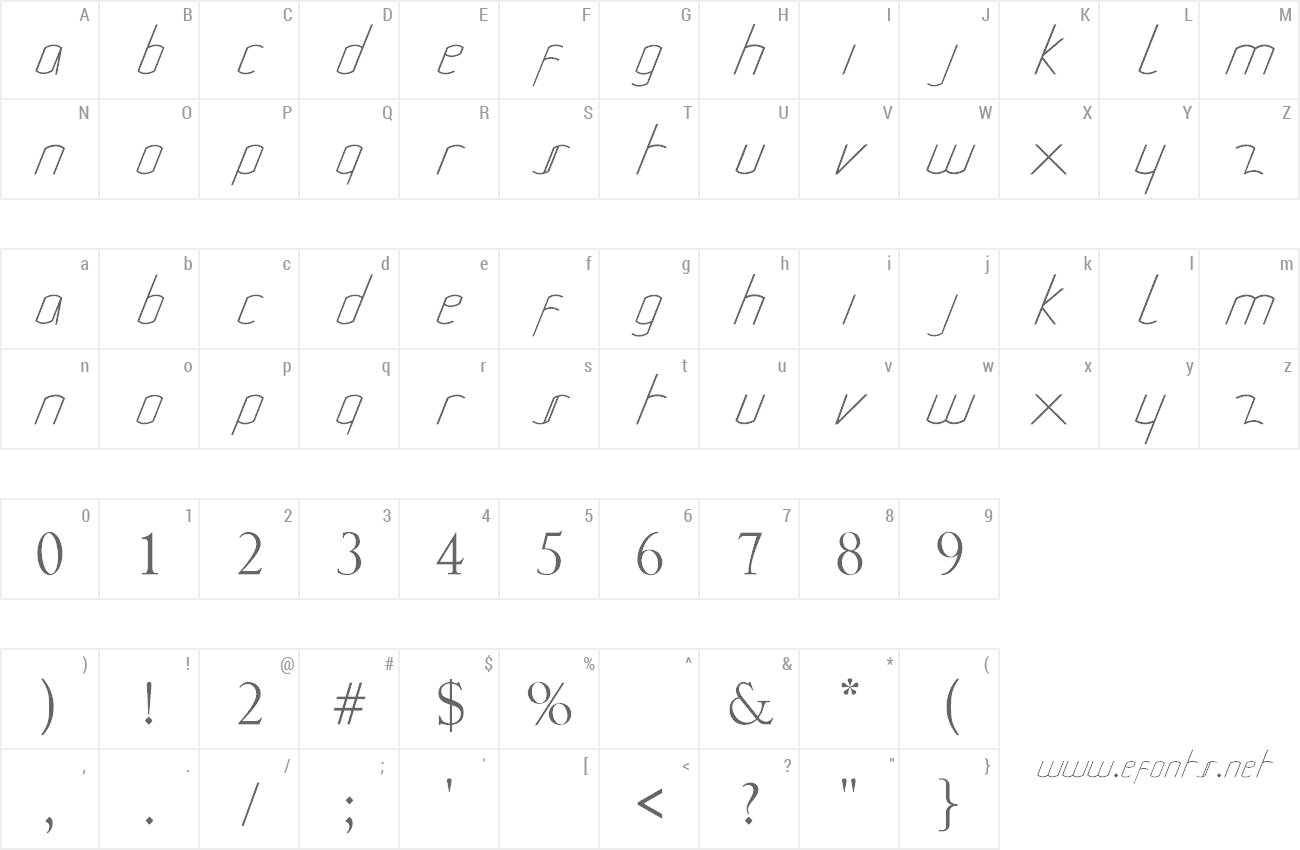
| Font name: | Miura Montes |
| Author: | Dnl Mnts |
| Note by Dnl Mnts | |
Fuente inspirada en caracteristicas del Lamborghini Miura. Creada para la Materia Diagramacion y Tipografia de la Universidad Icesi. Cali - Colombia. |